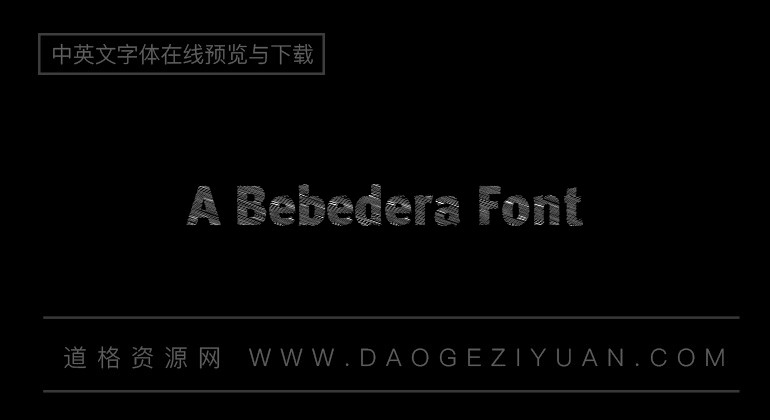
A Bebedera Font
A Bebedera Font是一款免费的无衬线字体,由设计师Marcelo Reis Melo创作。这款字体具有现代感和简洁感,适用于各种设计项目。它包括26个英文字母、数字和一些符号,可用于个人和商业用途。 该字体的设计灵感来源于巴西的手工酒瓶,字体的外形呈现出一种流畅和可读性强的感觉,非常适合用于海报、标志、包装设计、杂志排版等设计项目。
A Bebedera Font是一款非常不错的手写艺术字体,具有很好的视觉感,适合于文化类的宣传设计、商业类品牌的广告和产品包装设计以及个性化文字排版等较多场景。